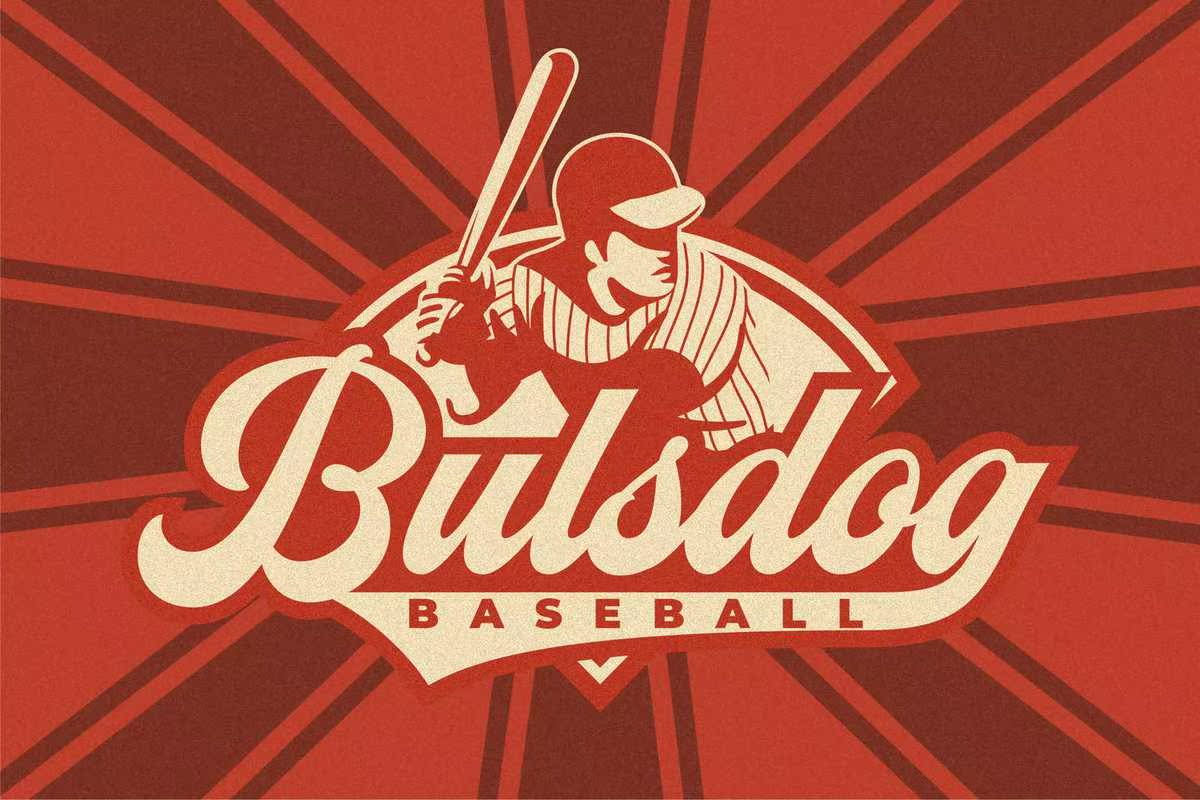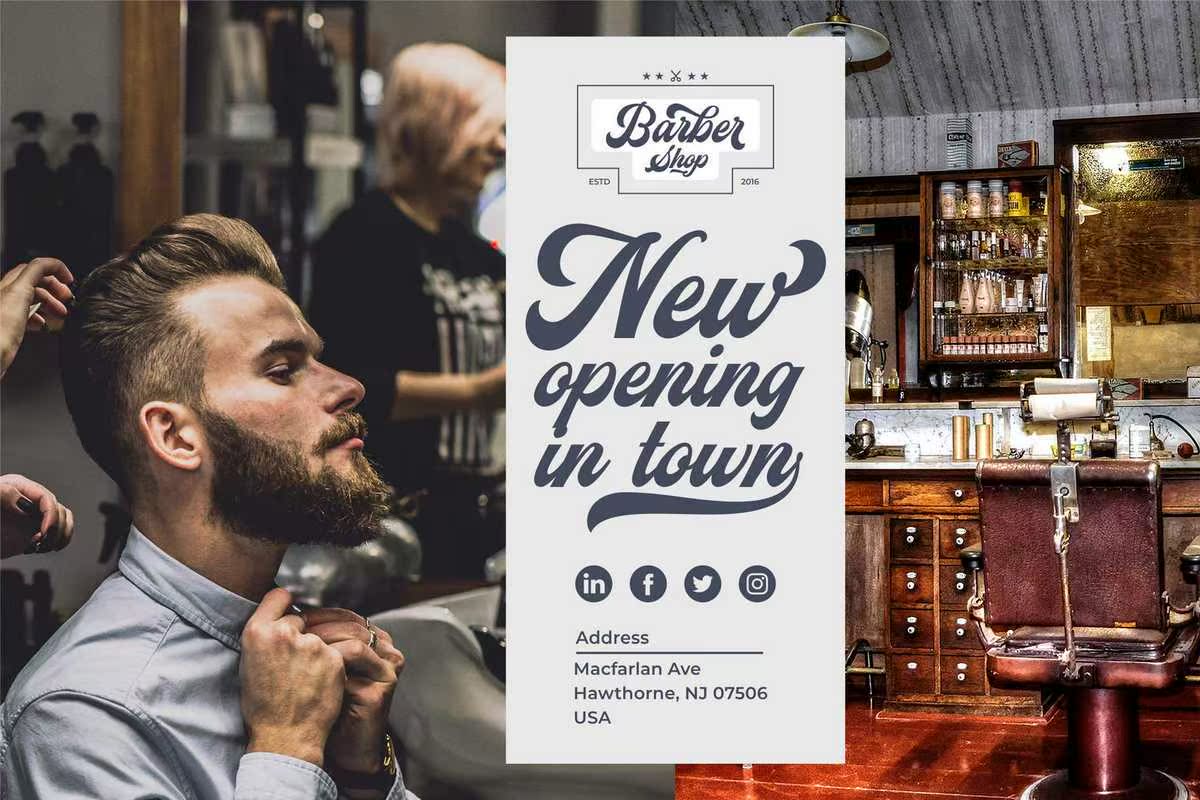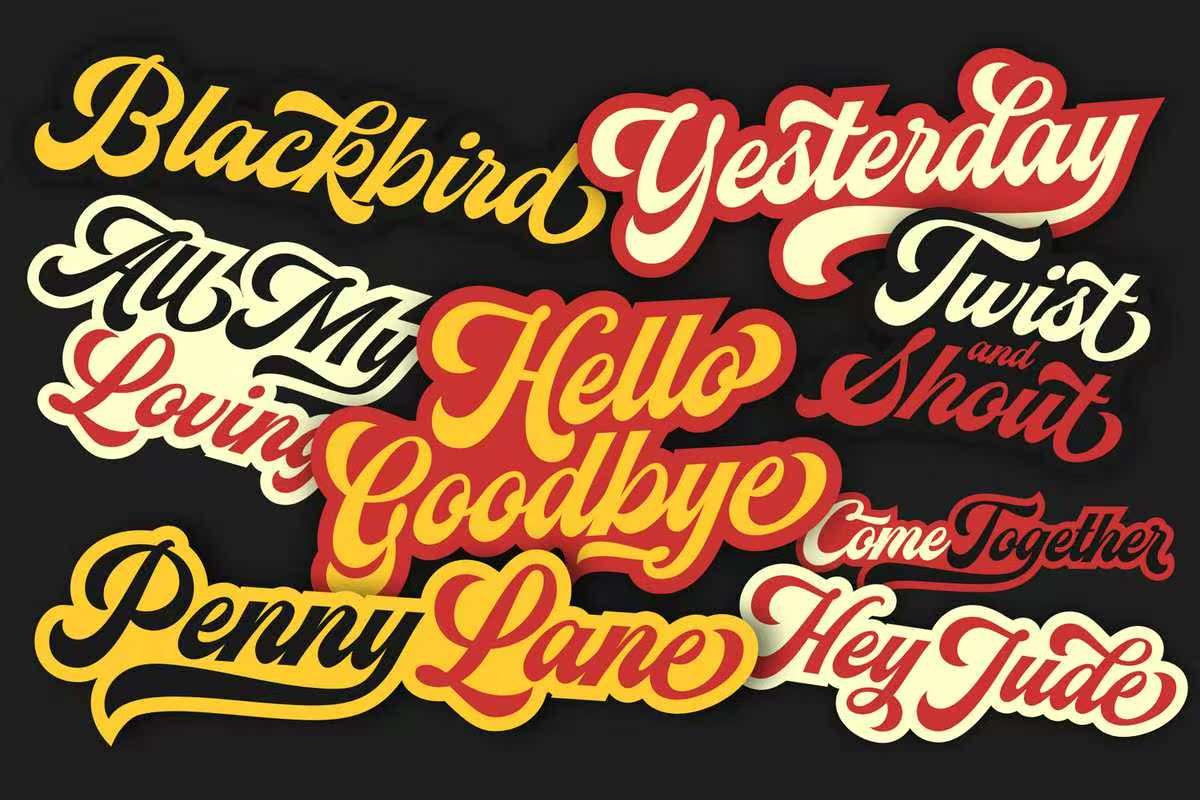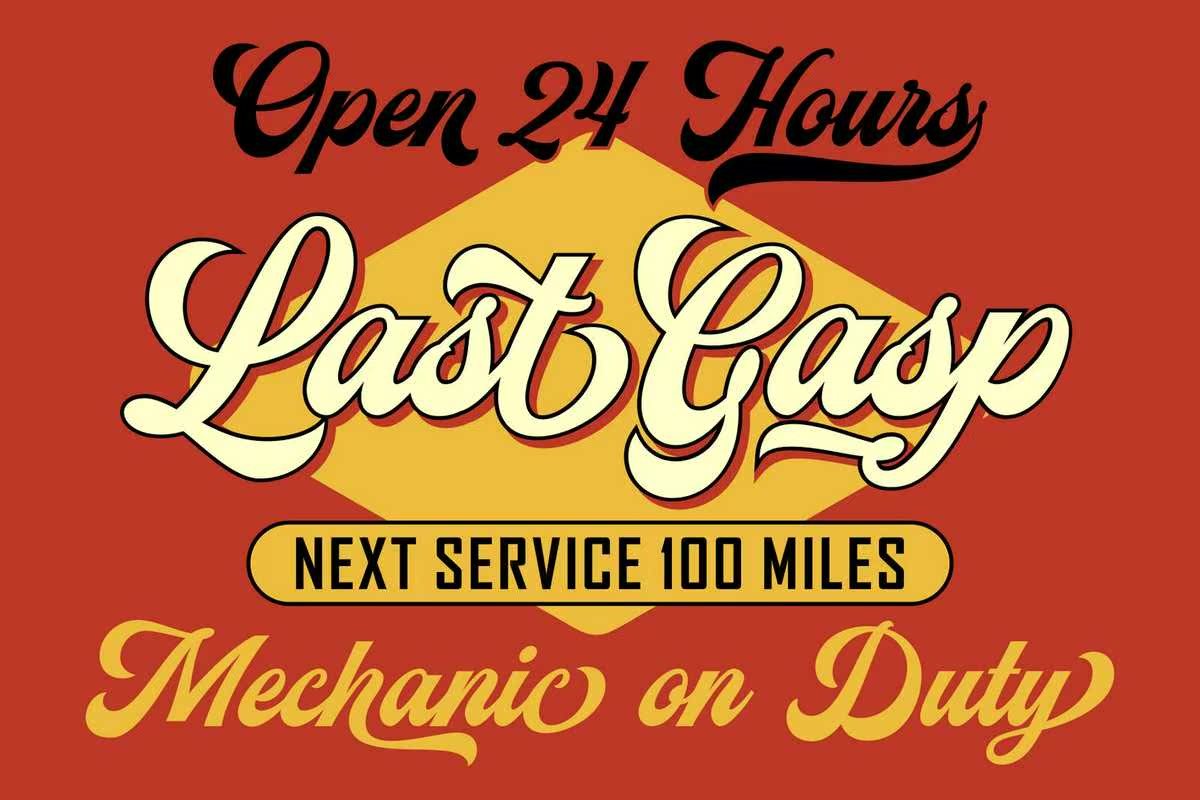
您好,街球字体,灵感来源于现代和现代的棒球运动。这款手工制作的防弹衣有几个精确的图层,总共有511个标志符号。街球非常适合使用各种媒体,例如:;包装、徽标、标签、海报、衬衫设计、quoteofwisdom、手写、排版和许多热媒体。嗨,街球字体,灵感来源于棒球运动,来自现代和葡萄酒等。这款手工设计的防弹衣具有多个精确层,共511个字形。街球非常适合使用各种媒体,例如:;包装、标志、标签、海报、衬衫设计、报价、手写、印刷和许多热媒。